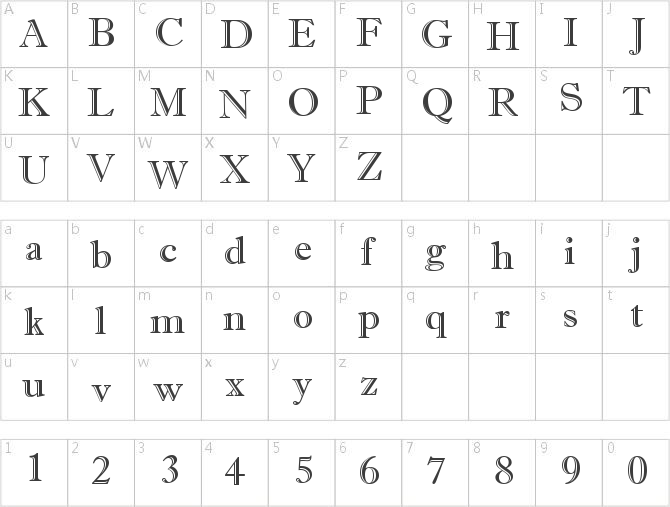
字體名稱: Imprint
Imprint-MT-Shadow
Imprint-MT-Shadow介紹
Imprint-MT-Shadow字體字庫是一款讓人賞心悅目、百看不厭的英文字體,適合各類廣告和產(chǎn)品包裝設(shè)計應用,字體大小0.05MB,格式為ttf字體,上傳用戶是woslxn,作者/版權(quán)方為未知